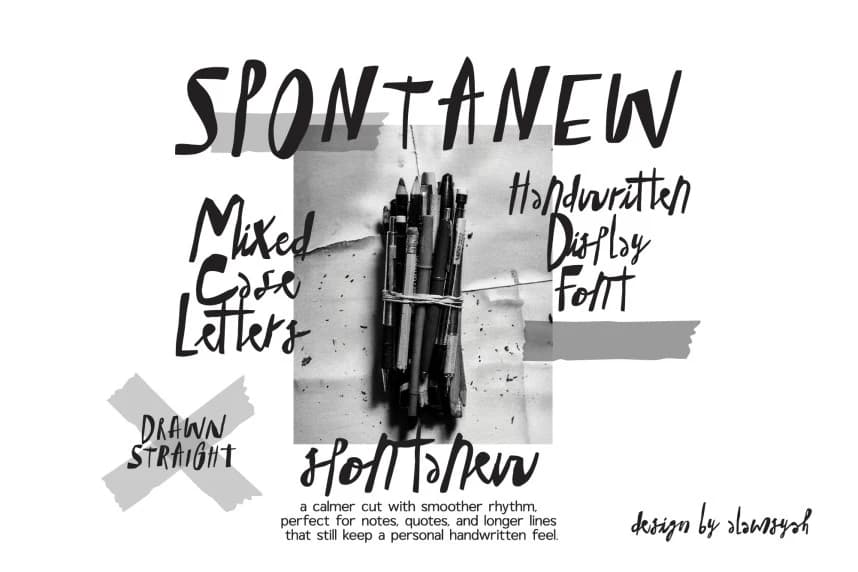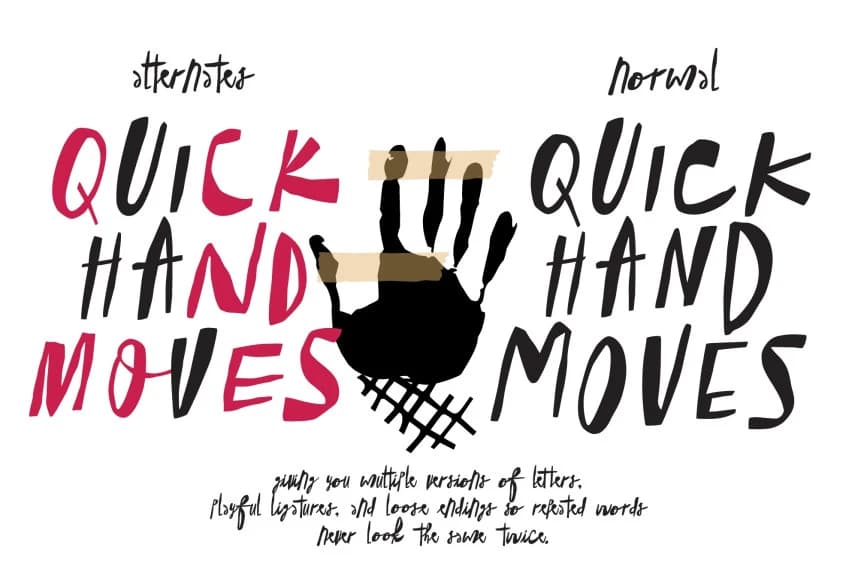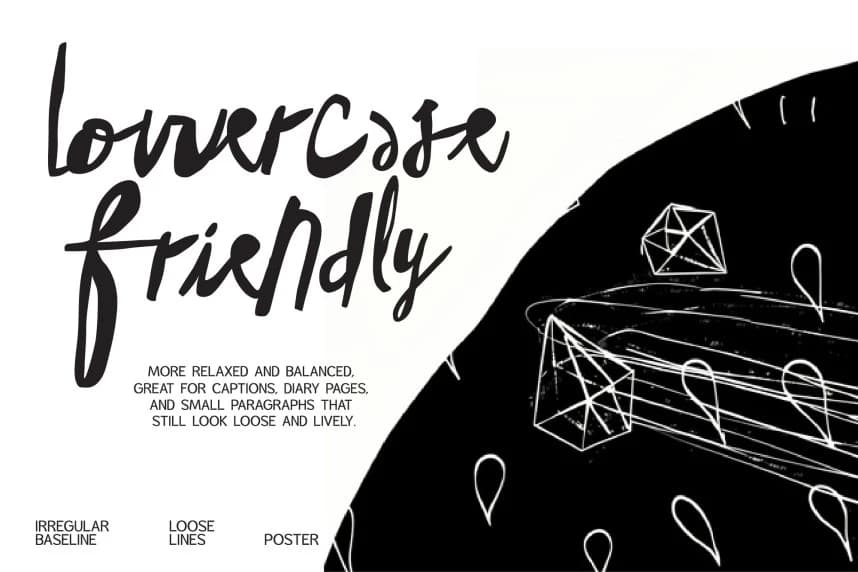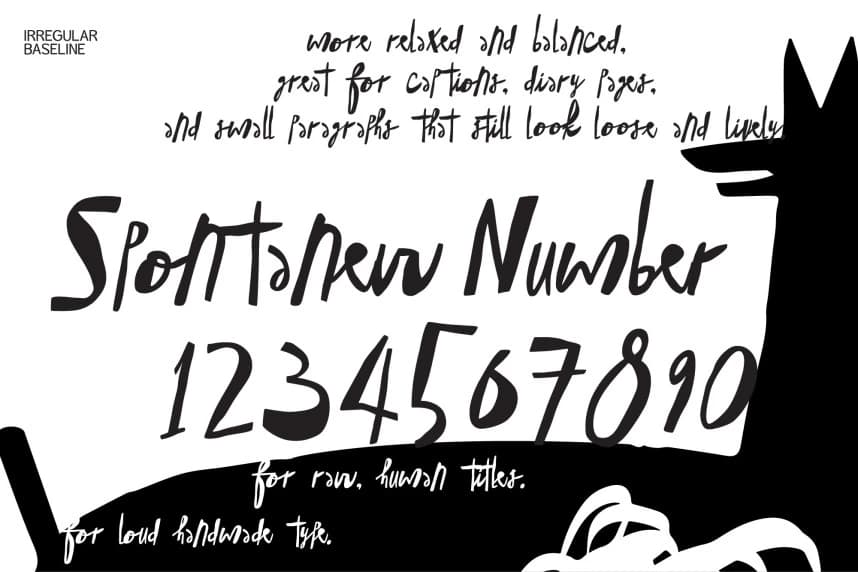
Spontanew Font
SPONTANEW Font, dinamik karışık büyük-küçük harflerle ve çift stile sahip, el yazısı bir gösteri yazı tipidir; doğal, özgün ve son derece kişisel bir görünüm sunmak üzere tasarlandı. Alıntılar, kişisel marka oluşturma, sosyal medya notları ve afiş başlıkları için, samimi, el ile çizilmiş bir görünüm
SPONTANEW Font, dinamik karışık büyük-küçük harflerle ve çift stillerle tanımlanan, spontane, otantik ve son derece kişisel bir görünüm sunan bir el yazısı gösterim yazı tipidir. Gerçek, elle çizilmiş bir hissiyatı talep eden alıntılar, kişisel marka oluşturma, sosyal medya notları ve poster başlıkları için mükemmel bir tercihtir.